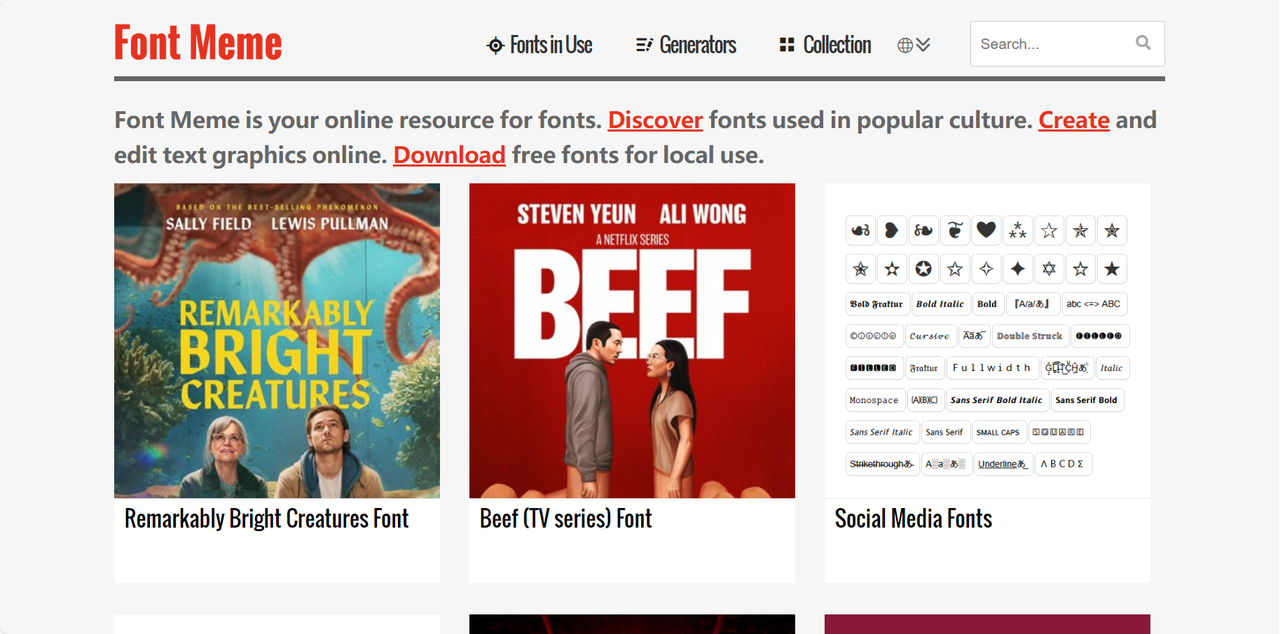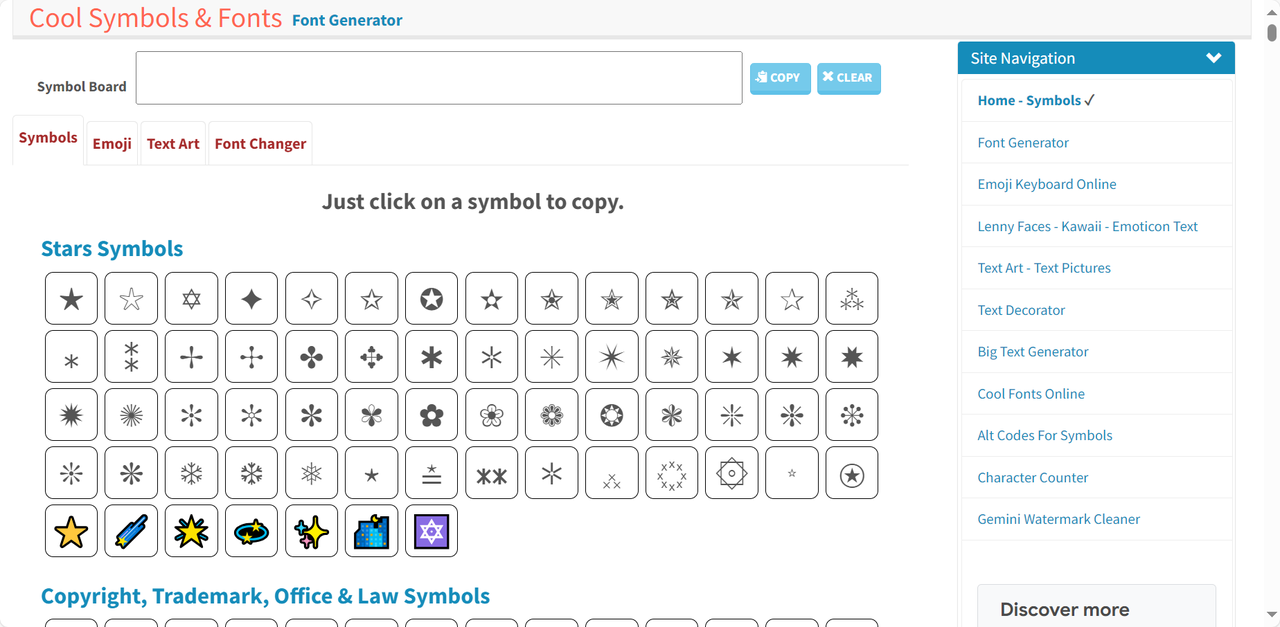
告别手动找字体!5 款免费花体英文转换器
花体字在一定程度上会让设计作品更加引人注目,而优质的花体英文字则能为作品增添高级感和设计感。是不是经常羡慕别人海报里的英文标题怎么那么好看,想自己手动找特殊字符排版,却达不到人家的效果。今天给大家整理了 5 款免费的花体英文转换器,从国内好用的字体管理工具到国外的优质小众工具,满足不同风格与场景的设计需求,一键完成花体英文转换,告别手动设计的烦恼,轻松打造吸睛的文字效果!跟着我一起来了解一下吧!
一、字由
作为国内知名的字体管理平台,字由依托其海量正版字体资源库,完美解决了花体字转换的需求,成为国内设计师打造花体英文的重要工具。它不需要你动手设计或者拼接字符,而是基于真实的花体英文字模板来完成转换,输出的文字效果更加精准和自然。操作过程非常简单,用户只需要在字由官网找到合适的英文花体字模板,点进进入字体详情页面,输入你想要的文字即可完成转换。如果你觉得这些文字效果不够绚丽,可以体验一下字由的 AI 字体功能,同样也是选择心仪的模板,点击做同款即可一键转换同款花体字、特效字,直接保存成透明背景的图片格式就能使用!
字由还有一点非常贴心,它的字体模板会定期更新,紧跟当下流行的设计趋势,还会根据当下的节日特性来提供对应的文字效果,比如六一儿童节前就会推出一些可爱风的花体字。为了解决大家最困扰的字体版权问题,字由内的每款字体都清晰标注了授权类型,用户可以按需进行选择。
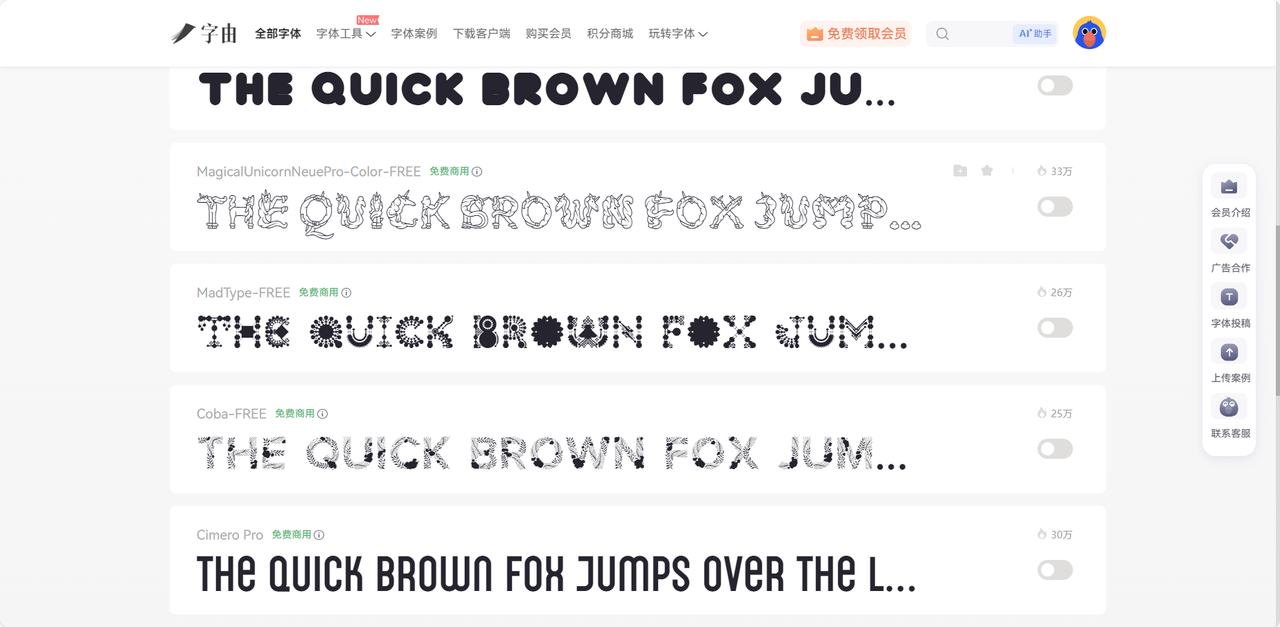
二、FontMeme
在国外众多的话题英文转换器当中,FontMeme 因为独特的创意模板成为了很多年轻设计师的常用工具。它提供了上百种不同风格的英文花体字模板,例如复古风、哥特风、涂鸦风、手写风、可爱风等等,满足用户不同场景下的个性化设计需求。值得一提的是,FontMeme 在字体转换方面给了用户充分的自由度,主打一个“创意定制”。也就是说,用户在输入英文内容之后,不仅可以在线选择花体字模板,还可以自定义修改文字颜色、背景,或者是添加阴影、立体、发光等文字效果。如果你觉得这样的花体字还是有些单调,FontMeme 还提供多种字体装饰符号哦,帮助你生成独一无二的花体英文字。生成的字体可以直接复制使用,也可以下载为图片格式,用户可以根据需求自行选择。这里的英文花体字模板大部分都是由设计师用户上传的,所以更新速度很快,你随时都能获取最新的字体资源,也能在这里轻松找到很多小众的花体字样式。需要提醒大家的事,FontMeme 免费版有一定的模板使用限制,部分热门且优质的模板需要付费才能解锁使用,不过免费版对于普通用户来说已经可以覆盖日常需求了。
三、Cool Symbol
Cool Symbol 是一款以简约便捷、轻量快速为特点的花体英文转换器,追求字体转换效率的用户一定要好好收藏起来!它的界面简单,没有多余的广告干扰,专注于特殊字符和花体英文字的快速生成,打开网页就能用,是名副其实的英文转换效率神器。
Cool Symbol 的操作流程也很简单,用户只需要在文本框输入英文内容,它会自动生成十几种不同风格的花体字效果,用户选择自己喜欢的字体复制即可。与其他工具不同的是,它生成的花体字都是纯文本格式,且兼容性极强,复制到任何平台都不会有乱码变形的问题,很适合用于制作社交媒体文案、昵称、聊天签名等场景。而且它完全免费,没有使用次数或者模板数量的限制,也就是说用户可以无限次生成花体英文,直到选到自己满意的位置。唯一的缺点就是字体风格覆盖不够全面,都是一些比较基础的花体字样式,偏爱复杂装饰花体字的用户可以选择别的转换器哦。
四、Lingojam
Lingojam 是一个拥有丰富的花体字模板和社区分享功能的平台,在花体英文字转换方面也非常有话语权。它最大的优势就是社区互动性,在这里可以上传自己设计的花体字,也可以套用其他设计师用户的花体字模板,说不定还能找到志同道合的设计师朋友哦。不过,由于字体模板都是用户自行上传的,某些模板会存在兼容性问题,复制到其他平台会出现乱码情况,大家注意一下哈。
Lingojam 的花体英文转换功能支持两种使用方式:一种是直接在平台挑选心仪的模板直接套用;第二种是自定义调整花体字的细节参数,实时预览文字效果。追求省事的小伙伴们可以直接选第一种,如果想打造独一无二的花体字可以尝试自行调整哦。总的来说,Lingojam 是一个实用的花体字英文转换器,更是一个创意分享平台,适合喜欢交流的小伙伴们来体验!
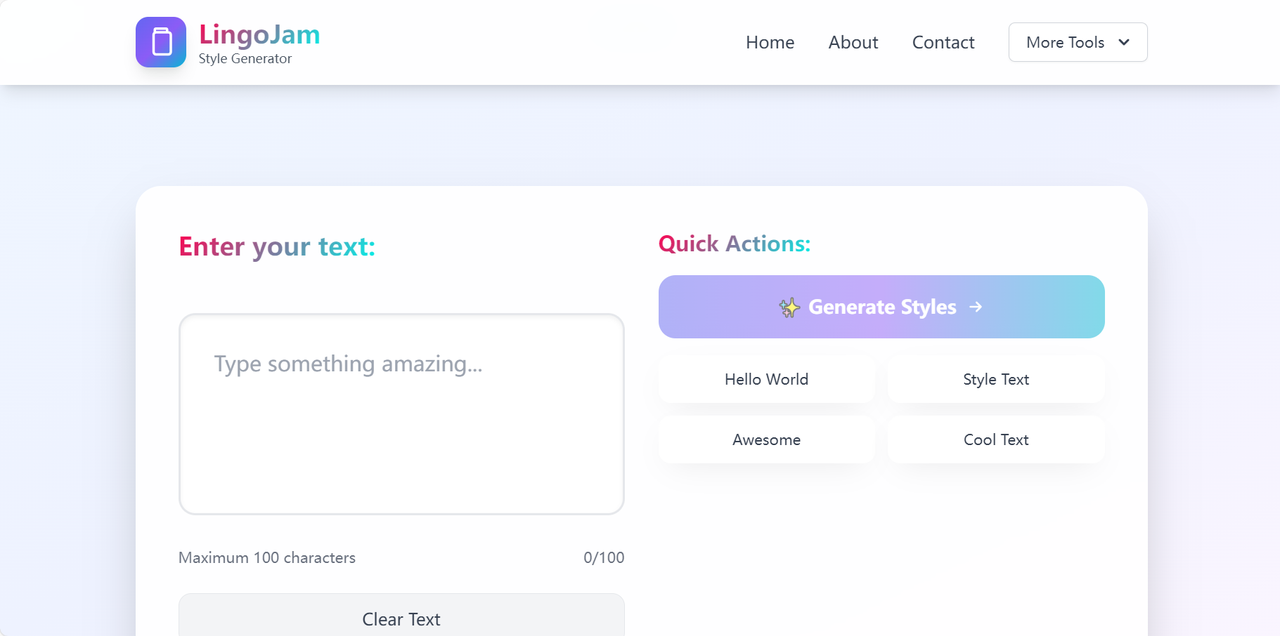
五、Fancy Text Generator
Fancy Text Generator 是一款国外老牌的免费花体英文转换工具,功能全面且效果稳定,能满足从简单到复杂的各种文字转换需求。除了支持在线转换花体英文字,还提供了多种特殊字符、特殊装饰和文字效果,帮助你打造出更加绚丽且美观的花体字。最关键的是,Fancy Text Generator 的稳定性很强,不会出现卡顿闪退等情况,生成的花体字兼容性也很高,适用多种场景。和 Cool Symbol 一样,该工具也不限制使用次数,全程免费无广告,是新手设计师的福音!目前,Fancy Text Generator 已经可以提供 50 余种花体英文字样式,包括常见的手写体、复古体,也有一些小众的镂空花体、霓虹花体等等,虽然字体数量不多,但贵在精致。对于文字视觉效果有追求的设计师们,Fancy Text Generator 的确是个不错的选择。
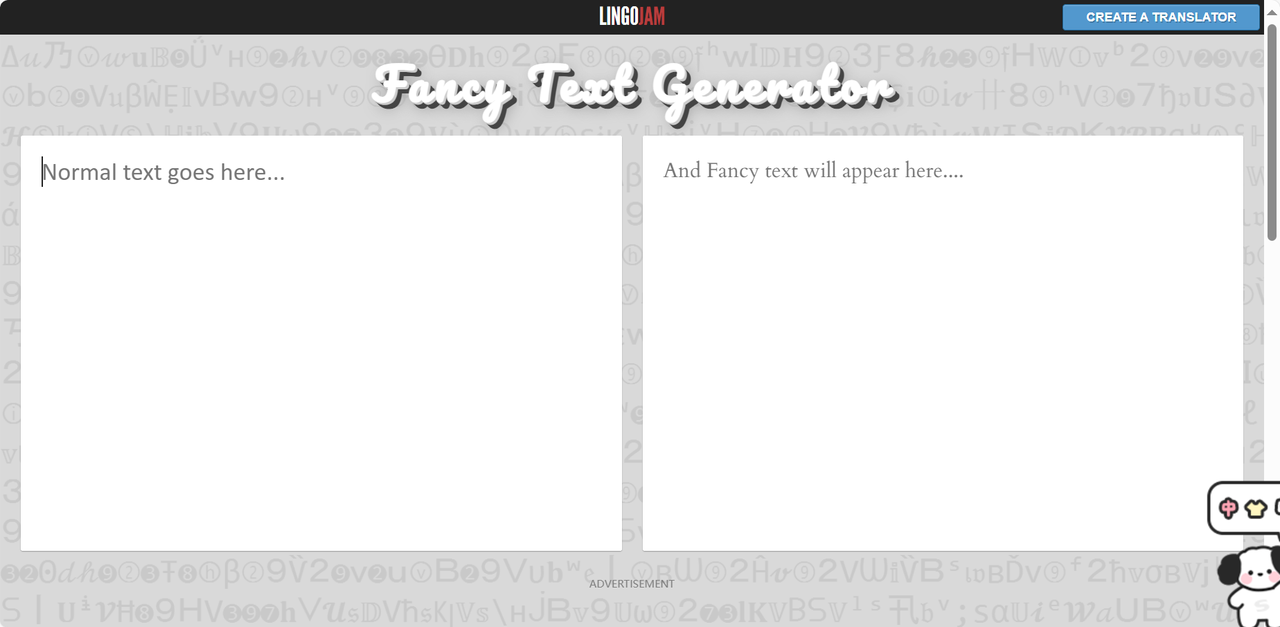
总而言之,本文推荐的这 5 款英文花体字转换器都有各自的特色优势,无论你是追求字体转换效率还是喜欢创意个性化的花体字,在这里你都能找到适合自己的工具。有了这些英文花体字转换器的帮助,无需自己手动排版拼接特殊字符,一键就能生成可以复制的花体英文,新手小白也不例外!而且这些工具都能免费无限次使用,对于预算不多的设计师伙伴来说也非常友好。赶快收藏起来去一一尝试吧,为你的作品增添不一样的色彩!